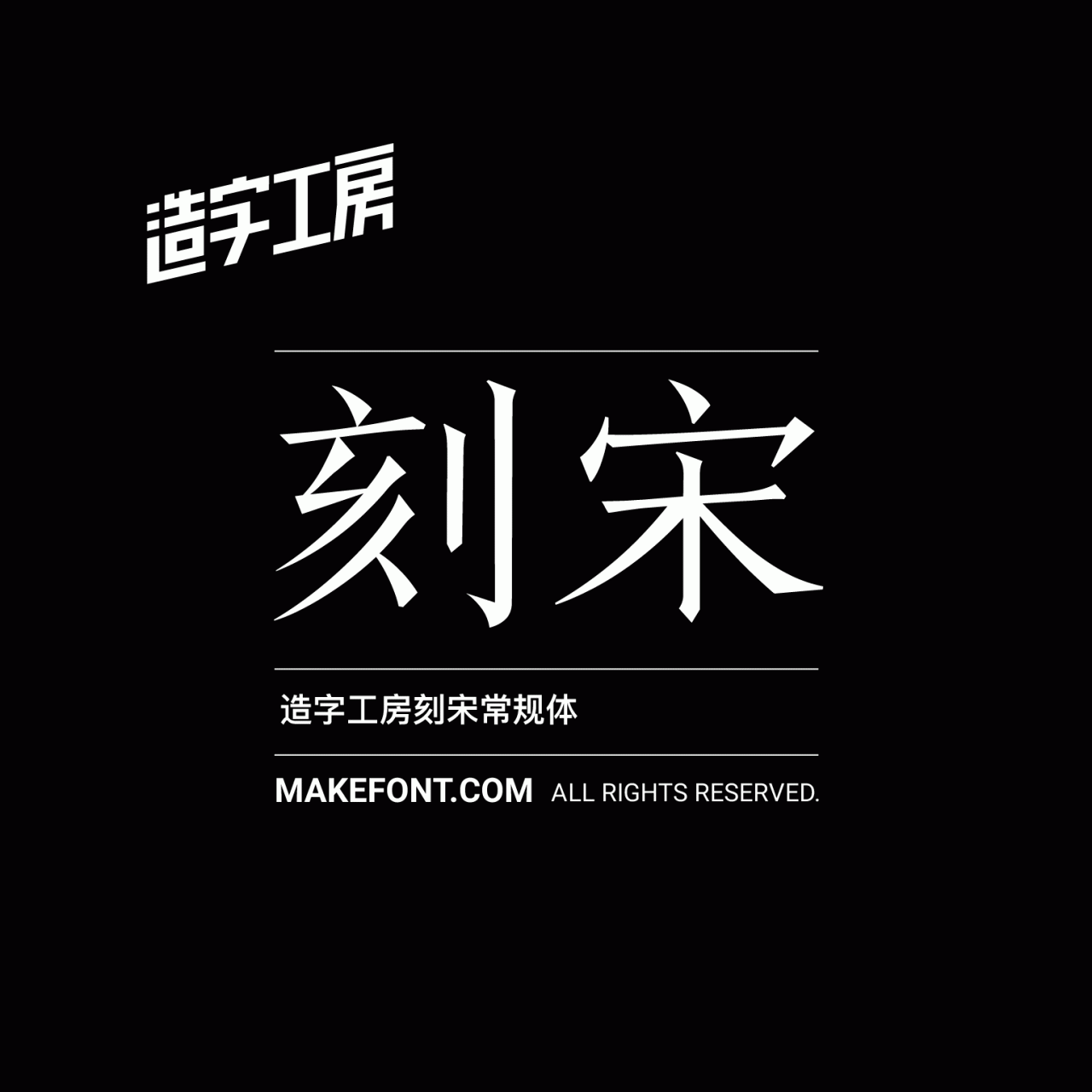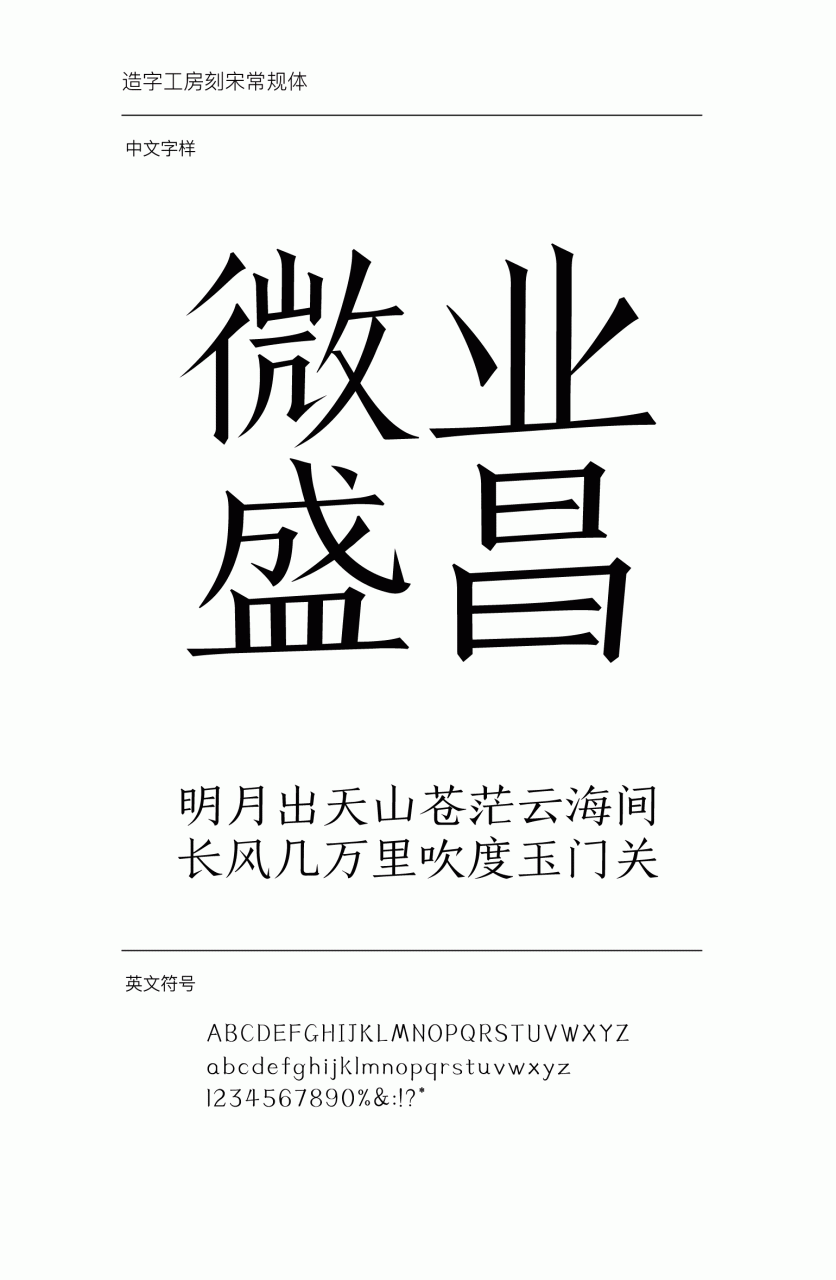
造字工房刻宋常规体
造字工房刻宋常规体设计说明
造字工房刻宋体,秉承古籍木版印刷之字形特性,笔画具刀刃之锋美,且造型秀美适意、刚柔并济,蕴传统宋体风格特性,在传统笔形间创新,结合当代设计视觉环境,易读性更强,在正文表现与品牌宣传上有很大的应用空间。 本字体为简体字库,采用OpenType/CID格式,Adobe-GB1-5编码。基于中华人民共和国GB2312-80字符集标准,另按需添加101个汉字。共收容字数6864CJK汉字,ASCII常用字符100个。